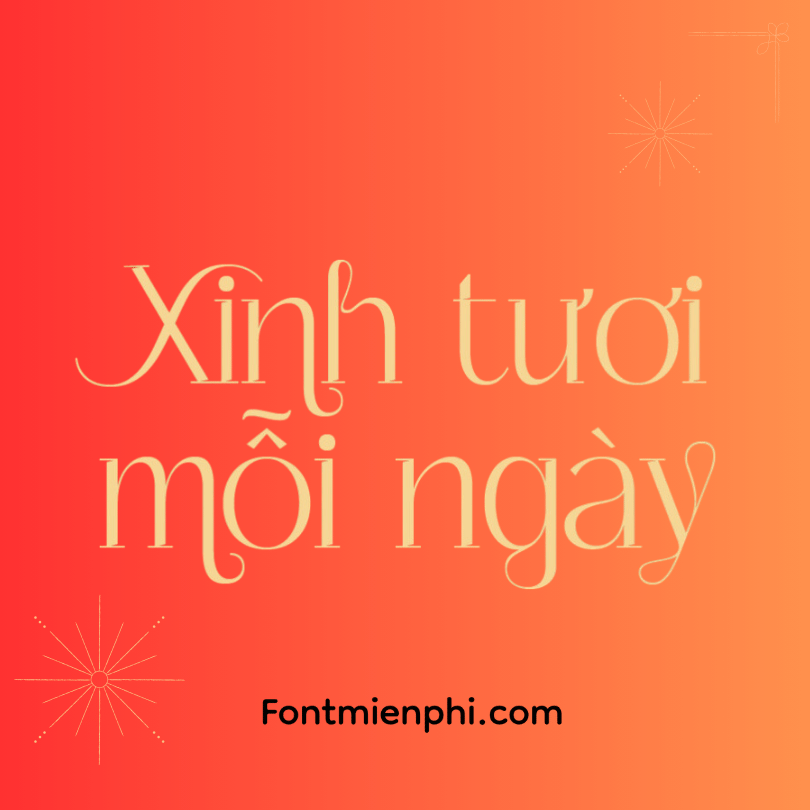
Font Việt Hóa 1FTV VIP Fairyland – Phong Cách Cổ Tích Mộng Mơ
Font 1FTV VIP Fairyland là bộ font chữ Việt hóa đặc biệt, lấy cảm hứng từ thế giới cổ tích với những nét chữ mềm mại, bay bổng. Phù hợp nhất cho các thiết kế:
• Sản phẩm trẻ em (sách, đồ chơi, quần áo)
• Thương hiệu cửa hàng bánh ngọt, café
• Thiệp mời, wedding, sự kiện
• Bao bì mỹ phẩm organic
ĐẶC ĐIỂM NỔI BẬT:
✔ Full bộ Tiếng Việt chuẩn Unicode
✔ 3 kiểu chữ: Regular – Bold – Shadow
✔ Dễ dàng mix với họa tiết hoa lá